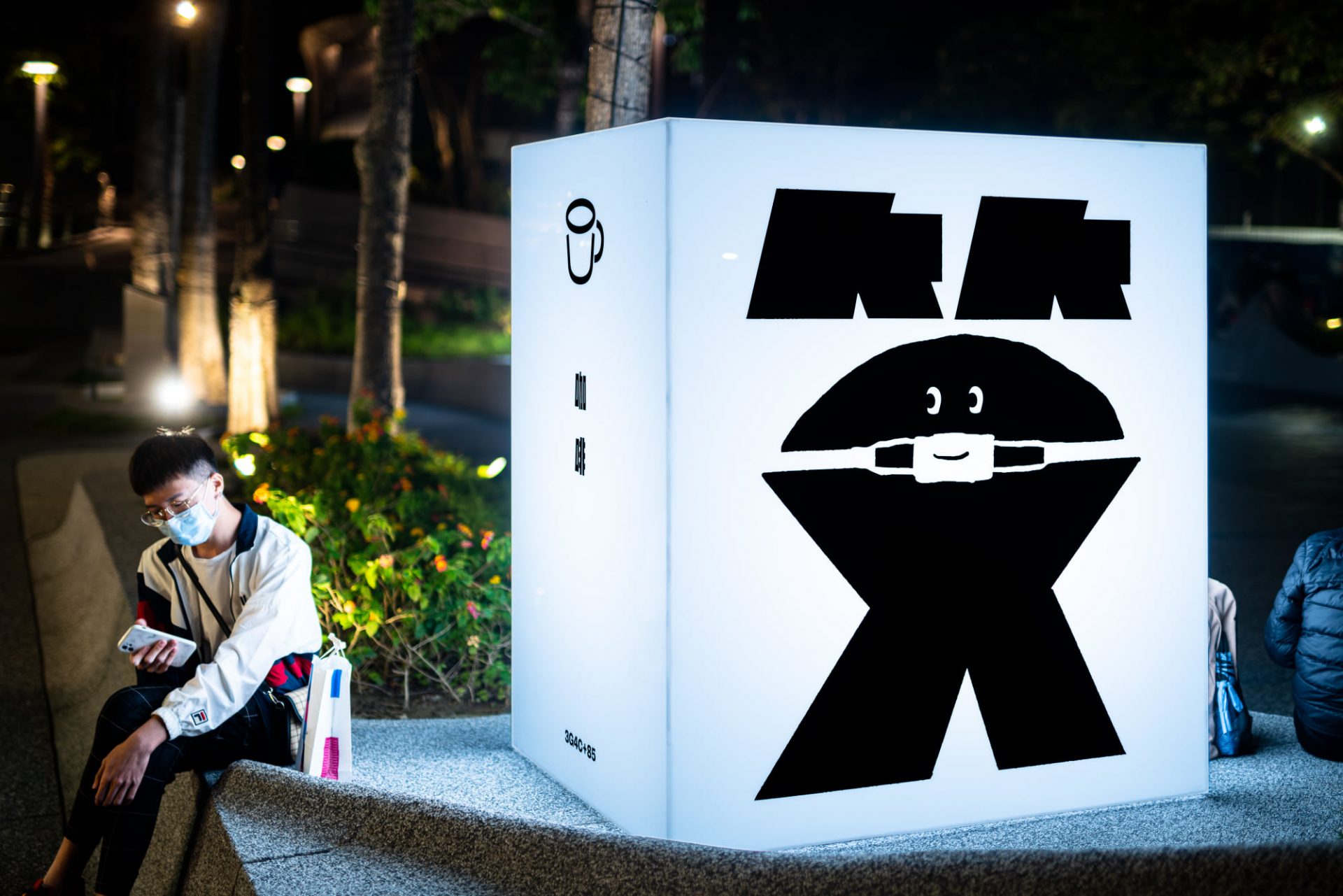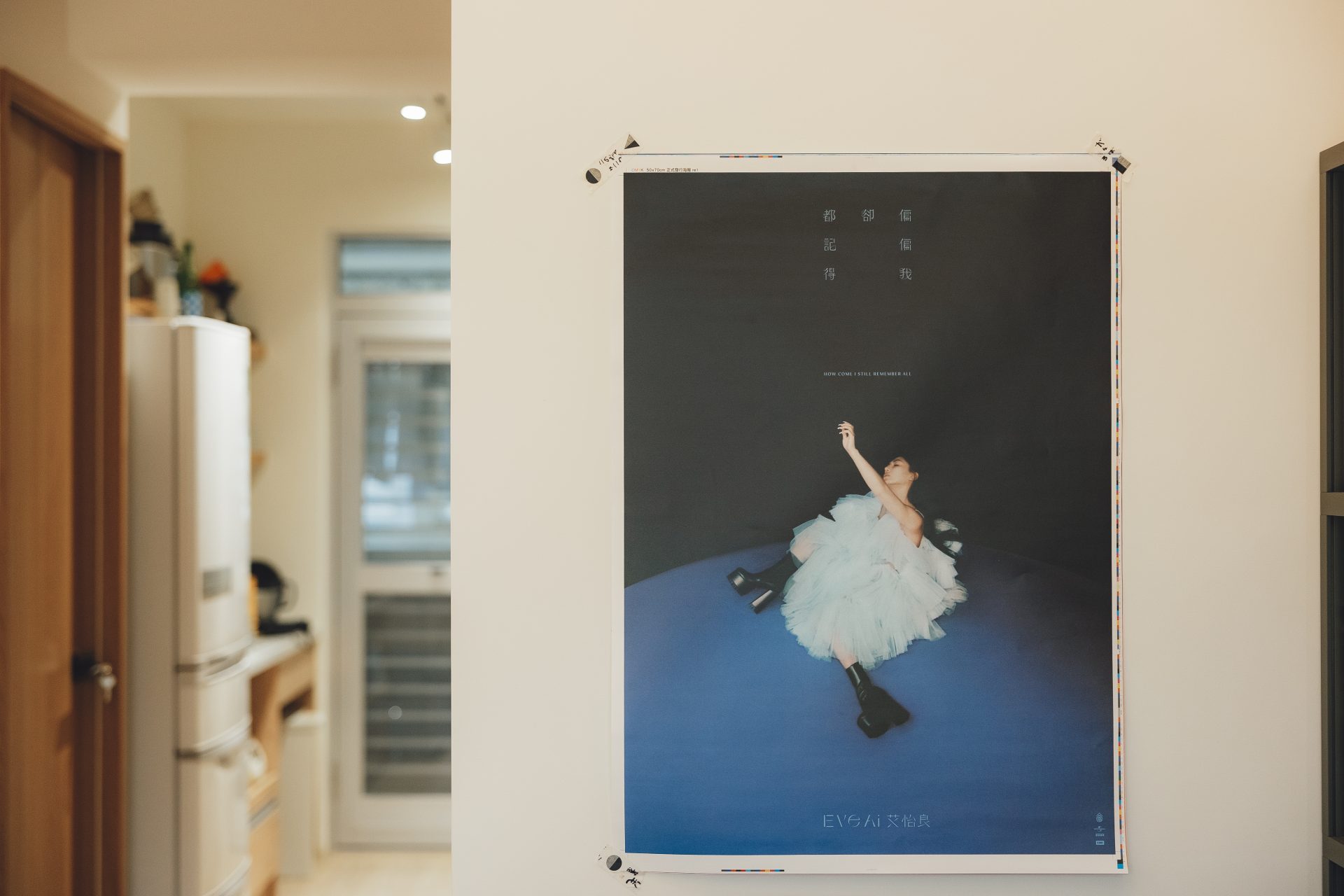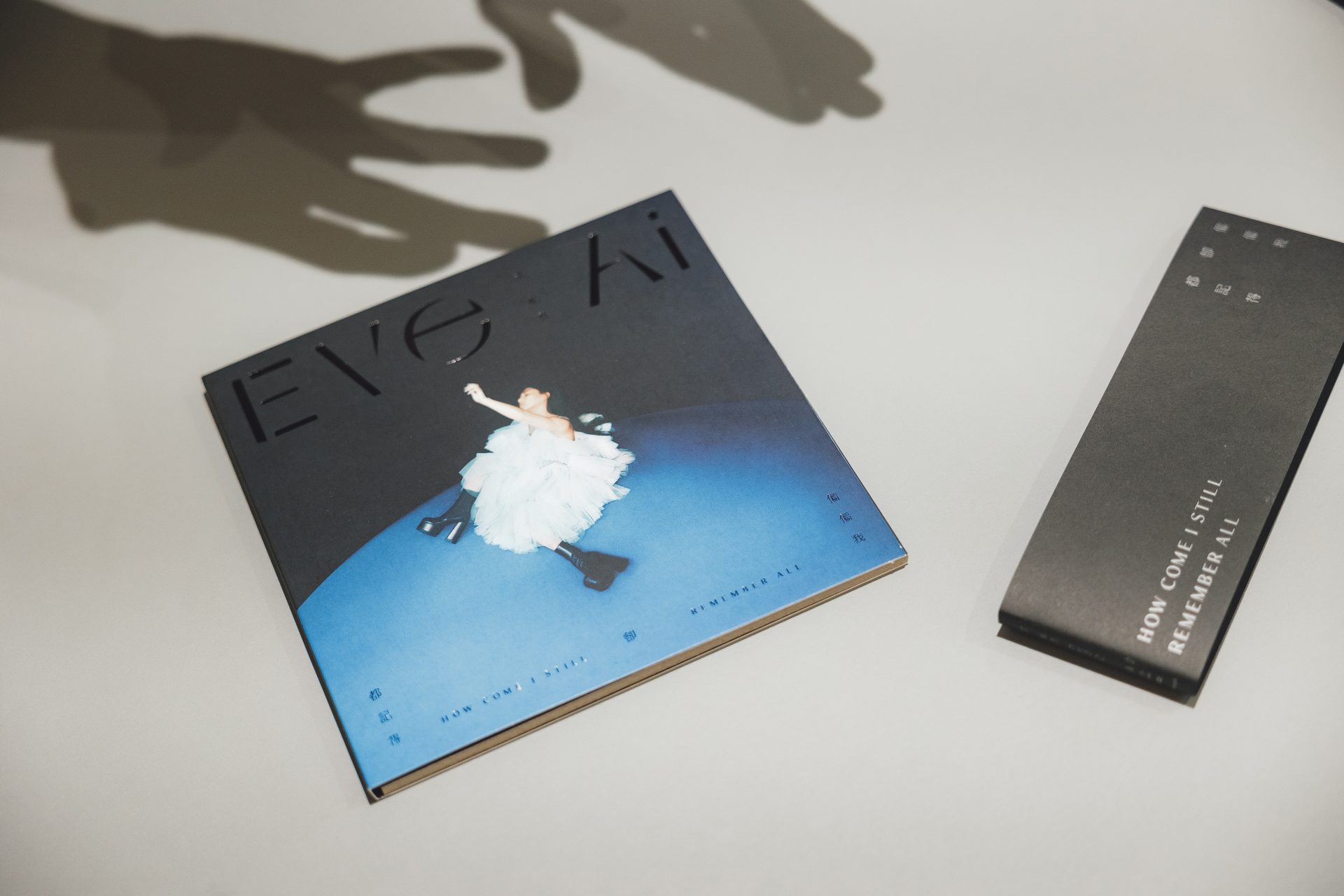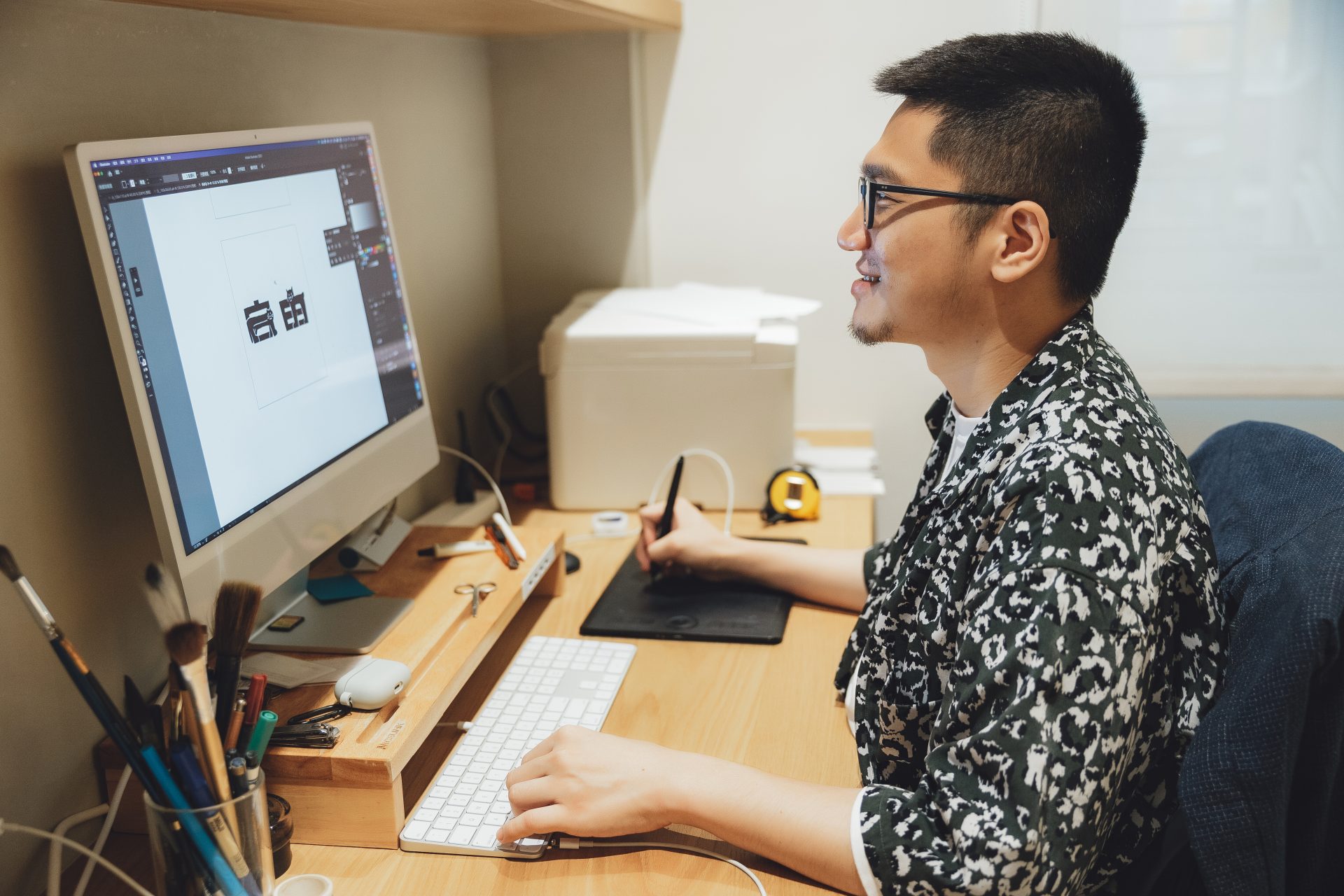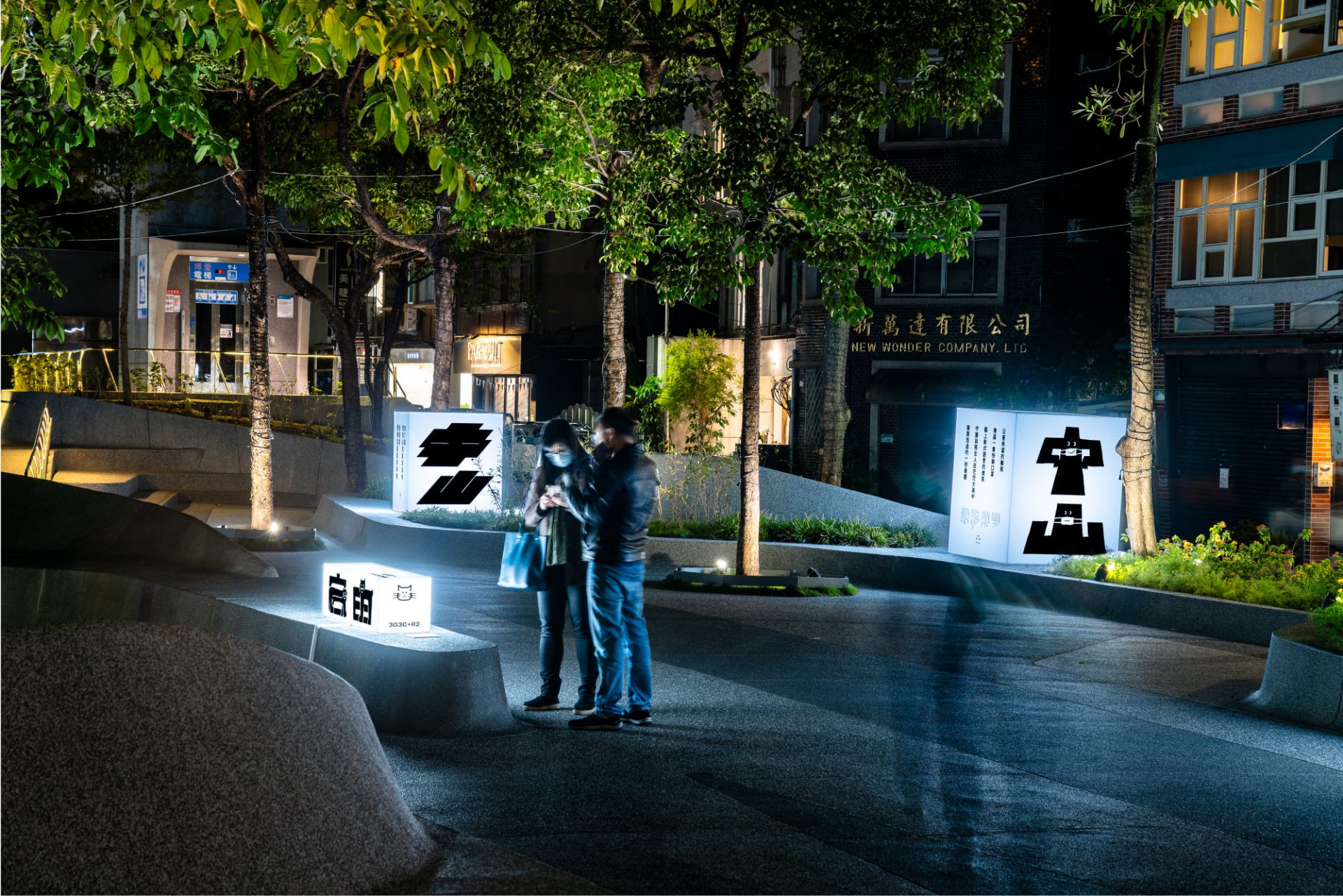
擅長做字的他,鑽研字體的起點是為「雪恥」?設計師宋政傑於一筆一畫間糾結完美,翻玩台灣字體桃花源!
在他的世界裡,文字從不單單只是書寫、傳達意思的工具,而是在一橫、一豎間都能賦予每個筆畫生命,創造出「文字」本身獨有的個性,不需要加上表情符號、不需要字字句句串連起意思,就能從中感受這些字的情緒與表情 — 以「字體設計」見長的設計師 宋政傑 ,讓「字體」在視覺上不再只是服務性、功能性的角色,而是真切傳達意涵與情境的藝術。
曾任職於設計和廣告公司,使他不只具備設計美感與技術,又能跳脫設計框架、兼容行銷與策略思維,身為這樣一個「設計圈裡的廣告人」,他確實總保有理性,透過平面和字體設計的美感孕育出更豐富的設計與商業價值,卻也笑說自己十分濫情,常將感性寄託於插畫傳遞心靈狀態,偶爾又將兩者交織,在曲折迴旋中任性創作,甚至透露如今之所以能夠遨遊字體設計之路,當初其實是為了「雪恥」 — 阿傑為什麼這樣說?且隨我們一探他的字體桃花源!
在設計汪洋中,找到適合自己的島嶼
走進宋政傑剛裝潢好不久的新家,不難發現架上除了有各種設計書、雜誌,還有一本本童趣的繪本,而宋政傑的創作啟蒙正是源自媽媽買的這些童話故事書,「我媽媽很喜歡買這些書,就連搬家也不准丟。」從喜歡畫畫到對設計產生興趣,都跟這些繪本有著密切的關聯,但設計產業何其廣,不知從何下手的他跟尋著當時眾人普遍的刻板印象 — 「室內設計很賺錢」,便在高中時選了這個學科,雖然上起課來也是有趣,但他總就覺得哪裡不太一樣,大學時隨著分發分數改讀工商業設計,但那份「不對勁」並沒有消失,為了找尋自己屬於什麼類型的創作者,便決定嘗試不同領域的創作,終究在旁聽應用美術系的平面設計課程後,挖掘到自己真正的喜好,後來還到了知名設計公司 洋蔥設計 Onion Design 實習、成為正職,從此踏上設計師這條不歸路。
聊著聊著,宋政傑在言談中突然爆出一句話,若說平面設計是他不斷摸索的結果,「那字體設計其實就是我『雪恥』的成果!」他說首次接觸字體的相關專案是在實習期間,雖然在設計、製作時就能感受自己並沒那麼有把握,但卻怎樣都沒想到在展示作品後,老闆會把他拉到一旁悄悄說:「阿傑,你是不是不擅長拉字體呀?你做得好醜!」,聽阿傑說到這裡,配著他誇張的表情,在場的我們都忍不住大笑,而阿傑則笑說聽到此番話的當下晴天霹靂,便從那刻起下定決心一定要做出「好看的字」,規定自己每天都要製作一組字、瘋狂練習。實習的最後一天,恰好再度巧遇與字體相關的專案發表,鍥而不捨的努力讓宋政傑終於有機會扳回一城,不只贏來一句「不錯喔!」,更發現了以往從未被開發的天份與興趣。
宋政傑的字體設計充滿表情與生命力。(圖片來源/宋政傑 Instagram)
雪恥成功,也從生活中發揮字體設計慧眼
談起宋政傑的字體設計,一定要帶大家先認識 2018 年於高雄舉辦的「好漢玩字節」。其中的「好漢市井」展覽中,首次擔綱展區設計的他,不希望只是單純依據主辦方提出的方向,製作和展示標準字,而是要能融合台灣特色、歷史與文化,以有趣、嶄新的視角打造專屬於這塊土地的文字桃花源。為了創作出獨有的字體氛圍,宋政傑從國外展望台灣,從過去旅行的記憶,觀察到日本街道喜歡使用圓體漢字、馬來西亞在同一塊告示牌上會出現五種語言、香港店家則是為了在各式招牌叢林中突顯自己而選用厚重的楷書。
那台灣呢?他發現相較於其他國家通常採直接音譯,台灣卻特別喜歡玩「諧音梗」,我們會為國外品牌、藝人賦予中文名字,如此有趣的差異,讓他決定依照這樣的文化脈絡替所有外來品牌換個名字,遵循它們原有的 Logo 特色轉換為以文字為主來表現的圖像,打造一個七彩霓虹的全新街道;為了讓觀眾更融入這個「商業」情境,並了解字體設計的排版細節,還透過一張張能讓觀展者互動及索取、別具生活感的「發票」,讓人細細品味其中的巧思。
宋政傑在 2018 年的「好漢玩字節」中打造出大玩台式諧音梗的《好漢市井》。(圖片來源/宋政傑 Instagram)
「我不希望做出有距離感的設計,而是想做能引起共鳴的創作。」— 宋政傑
今年的另一新作,他也善用對街道和日常風景的敏銳觀察,在今年的「臺北街角遇見設計」計畫中,以策展主題「厚臺北」出發,提煉中山一帶招牌的趣味,將採集成果結合詩作,於心中山線形公園製作一個個燈光和煦的街角文字裝置,替年末的心中山公園增添療癒內心的一點光:「中山是非常特別的地方,一出捷運站有極具現代感的百貨公司、大量的古著店、仿古時候書寫習慣的招牌、很有質感的文青選品店,這樣反差的對比是中山特有的城市樣貌。我進行了大量的招牌散步,並且採集了許多招牌、塗鴉、警告告示,我認為這些細小的角落構成這個街區的文化。」阿傑甚至在電腦中與講解他採集的各式招牌和字體,眉飛色舞地一一講解。
街景反映著一個國家的文化,宋政傑也善用對街道和日常風景的敏銳觀察,提煉中山一帶招牌的趣味,於心中山線形公園製作燈箱裝置。(照片來源 / 宋政傑 Facebook,攝影 / 洪子傑)
他並非在藝術創作中刻意添加平易近人的元素,由宋政傑的居家擺設、空間規劃中便能發現他相當重視「生活感」,從牆面到家具都選用溫馨的色調、簡潔的線條,「就像我的插畫一樣,不會太過於銳利或精緻,單純傳遞一個心情或狀態,我想要它粗糙時就粗糙、華麗時就華麗,這是我的任性。」,他又接著說:「我很喜歡關注其他創作者的生活,因為每個作品其實都是源自於生活的累積以及身處的文化。」
不只觀察他人的生活,他也聆聽對方的故事並將自己融入其中。近期宋政傑替歌手艾怡良設計全新專輯《偏偏我卻都記得》,當初為了完整演繹歌手想表達的意念,他將專輯反覆聽了一個月,「對我來說聽一張專輯就像在看一場舞台劇,一首歌則是一個篇章,專輯描述⼀個沒那麼⾃信的⼈談戀愛、總是想要變成對⽅喜歡的模樣,對我來說這是⼀個很痛苦、糾結的狀態,所以會希望讓⼤家感受到很多的不乾脆與迂迴。」這讓他決定替這張專輯的每首歌曲名稱都打造不同字體來表現,分別代表相異的意境,彼此卻又密不可分,「這次的風格與我平常較為粗獷的手寫字不同,而是纖細、俐落的曲線,就是為了讓字體風格更貼近歌曲本身的細膩情感。」
面對不同類型的專案,宋政傑也會切換不一樣的角度來思考設計模式,依照品牌的理念量身定做「像是艾怡良的專輯,原本已經想了自己覺得很好的概念,但當我看到攝影師周墨所拍攝的照片時,就決定全部推翻、重新提案,」他接著補充:「並不是原本的很糟,⽽是我覺得就是差那⼀點,我希望我的設計能讓大家對這張專輯的體驗更完整,而非是個漂亮卻突兀的設計。我不要為了帥而帥,而是因為它帥而讓它帥。(笑)」
「我覺得設計是減法,將腦中想法不停精簡,才能創作出一眼就能打中人心的作品;插畫則是加法,在繪製過程中不停堆疊、想像,打造一個充滿有趣的世界。」— 宋政傑
從無數糾結中,自尋完美解方
雖然繪本開拓了宋政傑對畫畫世界的各種想像,但他卻說直到國小都很排斥閱讀這類的書籍,反而喜歡看有大量文字的金庸小說或《哈利波特》,「我覺得透過文字想像的畫面更豐富,那樣的世界才有無限的可能性,像現在聽客戶講述企劃概念時,腦中也直接會產生各種想法。」隨著生命歷練的成長,宋政傑演變出適合自己的創作模式,就連工作工具也都有他獨門的使用方法。
宋政傑憶起人生第一個繪圖板,說是在高中時擁有,但他當時不太習慣繪圖板的使用方式,便將它塵封了起來,沒想到大四實習時,發現同事人手一台繪圖板,「他們跟我分享一個很妙的理由,因為平常沒有在使用繪圖板的人基本上都不太會操作,當旁人想試著直接調整我們的設計時根本不知道從何下手,這時主導權就會回到自己身上,哈哈哈!」這番有趣、對設計師來說又吸引力十足的理由,讓宋政傑決定再度挑戰用繪圖板創作,也讓他在這個許多創作者都改用繪圖螢幕工作的時代,仍然選擇使用 Wacom Intuos Pro 繪圖板創作,並且補充了另一個原因:「我覺得做設計時是要維持一段距離的,這樣才能準確投射大眾看到我的作品時會產生什麼樣心境感受。」
現在的他已經把操作繪圖板練到了爐火純青的境界,不僅連出國也會帶上它,甚至笑說「滑鼠是什麼」,挪移檔案、傳圖片都用繪圖板完成,還透露了他的操作撇步:且我都只用繪圖板操控!通常大家都設定鏡射的移動模式,而我是選擇滑鼠模式,所以其他同事用我的繪圖板也變得不太會操作,決定權都在我(大笑),我也覺得用滑鼠模式比較快速,可以提高我的工作效率。」
相當注重操控性的他,除了讚許 Wacom Intuos Pro搭配的數位筆 Wacom Pro Pen 2非常好上手,也提到數位板上的 ExpressKeys™ 快捷鍵、觸控環和筆側開關,讓「人生沒有滑鼠」的宋政傑可以設定多種替代功能鍵,沒有滑鼠照樣能擁有滾輪模式,因此不僅在工作時使用,就連休閒、看片時都用繪圖板點擊,「因為真的太常使用了,可以看到我的使用痕跡非常明顯。」
問宋政傑覺得自己用 Wacom 創作了什麼樣的世界?他先是細數包含艾怡良新專輯《偏偏我卻都記得》、近期的「2021 臺北街角遇見設計」燈箱裝置作品,以及文策院參與美國電影市場展的主視覺都是用 Wacom 完成的,也不改幽默地笑道:「我用 Wacom 創作了⋯⋯ 好多錢!(大笑)畢竟它就是我工作、生財的必備工具啊!」除了工作上的使用,抒發心情的插畫也不例外,不只是在板上直接拉出線條,偶爾也會手繪塗鴉,再上傳到電腦用繪圖板繼續後製。
不過話說回來,宋政傑認真想了想,說道:「我自己是個很糾結的人,在滑動游標時其實都是各種猶豫跟懷疑,在筆觸或動作點下的那一刻,就像是在糾結中的一種選擇。」對宋政傑來說,不論是做字體、平面設計或插畫創作,每個過程必然存在眾多糾結與抉擇,而他所認為的「完美」都僅存在於當下,每一個作品都是彼時條件中所能形塑的最好結果,也可以這麼說吧!宋政傑在他的創作中打造了迂迴糾結裡的完美,一個能容納自我與創意的桃花源
「以前很常被問想要成為什麼樣的創作者,那時的我根本回答不出來,現在的我則想當位『把設計做好的創作者』,能兼顧細節、創意、視覺的設計師。」— 宋政傑